فونت لاتین De Luxe Next
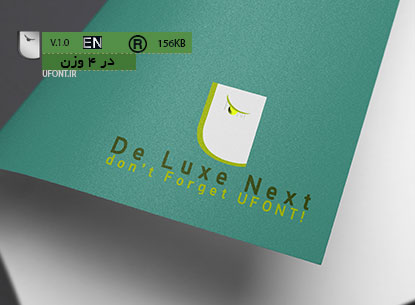
دانلود فونت لاتین De Luxe Next ، نشر 2019
فونت جدید و کلاسیک لاتین با ساختار لوکس و مناسب برای استفاده در طرح های خاص
یکی از مهمترین ویژگی های این فونت خوانا بودن و ساختار بسیار ساده است که موجب شده برای استفاده در متن نیز مناسب باشد ، این فونت ، امسال بصورت رسمی در 4 وزن منتشر شد که هم اکنون می توانید آن را از یوفونت بصورت رایگان ، دریافت کنید ، با ما بروز باشید ! 🙂
فونت لاتین مجموعه دزدان دریایی کارائیب
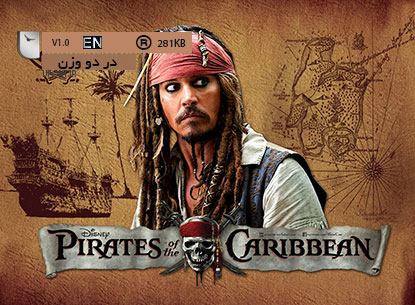
فونت لاتین مجموعه دزدان دریایی کارائیب
فونت لاتین مجموعه فیلم های دزدان دریایی کارائیب ، این فونت زیبای لاتین ، که جزو فونت های خاص دسته بندی میشود نیازی به توضیحات اضافه ندارد ، هم اکنون فونت لاتین مجموعه فیلم های دزدان دریایی کارائیب با همین نام یعنی : Pirates of the Caribbean از یوفونت در دسترس است
دانلود مجموعه فونت و آیکن hello christmas
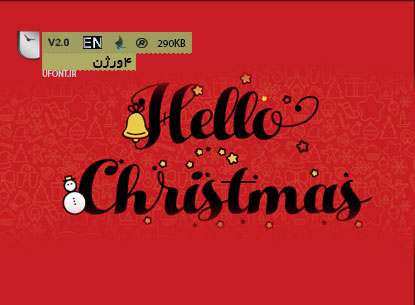
دانلود مجموعه فونت و آیکن hello christmas
دانلود مجموعه فونت و آیکن hello christmas ، مجموعه ای بی نظیر شامل آیکن ، فونت و سمبل های مناسبتی کریسمس
فوق العاده با ارزش ، کاربردی و کمیاب ، با توجه به نزدیک بودن کریسمس مطمئنا برای طراحان عزیز این دست فونت ها بسیار کاربرد دارد
این مجموعه شامل آیکن های مربوط به کریسمس در دو وزن می باشد و بصورت وکتور تا اندازه بی نهایت بدون افت کیفیت قابلیت بزرگنمایی دارند
پیشنمایش فونت
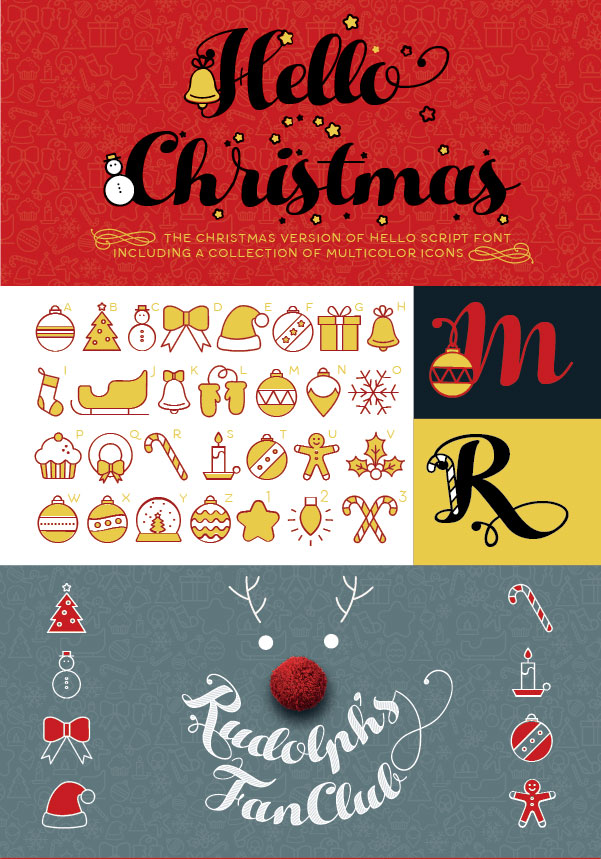
دانلود مجموعه فونت و آیکن hello christmas
-مناسب طراحی آیکن های سایت
-مناسب طراحی های مناسبتی کریسمس
-ساختاری پیچیده و گرافیکی
-مناسب تایپوگرافی
دانلود فونت miraculous and christmas
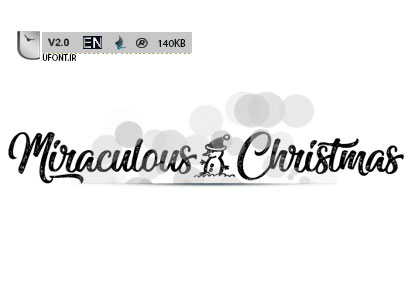
دانلود فونت miraculous and christmas
دانلود فونت miraculous and christmas ، فونتی مناسبتی با اِلِمان های مربوط به کریسمس و هم چنین ساختاری پیچیده با استایل دستنویس
در فونت miraculous and christmas حروف کوچک و بزرگ با هم در ارتباط می باشد پس هنگام استفاده از این فونت حتما به نحوه استفاده از حروف کوچک و بزرگ دقت نمایید چرا که تاثیر بسیاری در خروجی کار دارد همچنین فارق از گرامر و دستور زبان میتوانید به صورت سلیقه ای در طراحی حروف کوچک یا بزرگ را انتخاب نمایید ( فقط جهت طراحی) این راهکار مناسب است و برای نوشتاری بهتر است قواعد گرامر و دستور زبان رعایت گردد
این فونت دارای سمبل های مناسبتی کریسمس نیز می باشد
دانلود فونت فیلم transformers (تبدیل شوندگان)
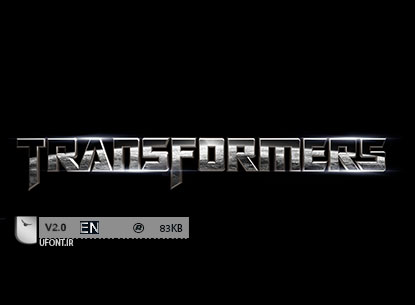
دانلود فونت فیلم transformers (تبدیل شوندگان)
دانلود فونت فیلم transformers (تبدیل شوندگان) ، فونت بکار رفته در لوگوتایپ فیلم تبدیل شوندگان را میتوانید هم اکنون از بروز ترین مرکز دانلود فونت دریافت نمایید
دانلود فونت رسمی جام جهانی 2018 روسیه
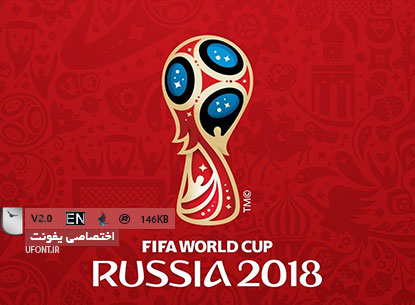
دانلود فونت رسمی جام جهانی 2018 روسیه
دانلود فونت رسمی جام جهانی 2018 روسیه فونت لاتین رسمی مربوط به پوستر ها و کارهای گرافیکی جام جهانی 2018 روسیه هم اکنون از یوفونت در دسترس می باشد
این فونت بصورت رسمی از طرف فیفا در پوستر تایید شده مورد استفاده قرار گرفته و نسخه ای که از یوفونت منتشر می گردد فونت رسمی و بدون دستکاری است که بصورت رایگان در اختیار مخاطبین عزیزمان قرار می گیرد ، نام این فونت Dusha می باشد
ساختار این فونت استاندارد و فانتزی است و چینشی فوق العاده حرفه ای و زیبا دارد
فونت رسمی لوگوتایپ شرکت یاهو
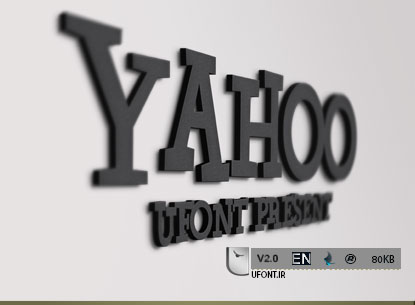
فونت رسمی لوگوتایپ شرکت یاهو
فونت رسمی لوگوتایپ شرکت یاهو ، فونت رسمی استفاده شده در لوگو و لوگوتایپ شرکت یاهو ، این کمپانی محبوب را تقریبا همگی می شناسند و در روز چندین بار به لوگو این کمپانی برخورد می کنند
هم اکنون فونت لوگوی یاهو YAHOO در اختیار شماست ، ساختار این فونت نا متعارف است و کلمات با چینش فانتزی و کمی به هم ریخته در کنار یکدیگر جای می گیرند اما به لطف طراحی اصولی ، در پشت صحنه و عدم خروج از نظم و یکپارچگی تعریف شده برای یک نوشته با نگاه به این به هم ریختگی زیبایی را در قلب این بهم ریختگی می بینید
طراح این فونت با اصول طراحی بسیار آشنا بوده است و در کل فونتی عالی با چینش منظم از خود به یادگار گذاشته است که در دسته فونت های فانتزی لاتین قرار می گیرد ، لذت ببرید
فونت لاتین PowerFull
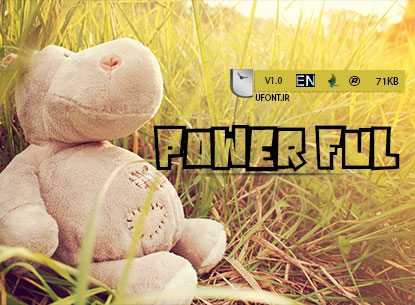
فونت لاتین PowerFull
فونت لاتین PowerFull ، فونت خاص و کاربردی ، دارای ساختار فانتزی و کلمات به هم چسبیده و تو خالی
این دست فونت های فانتزی ویژه طراحی هستند و در کارهای گرافیکی بسیار بکار می آید ، پس این فونت زیبا را از دست ندهید
فونت فارسی فانتزی (پکیج)
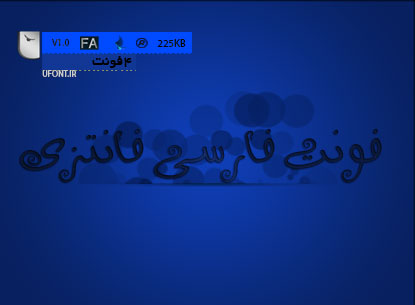
فونت فارسی فانتزی (پکیج)
فونت فارسی فانتزی (پکیج) ، مجموعه 4 عدد فونت های فانتزی با ساختار کودکانه فونت هایی خاص که مطمئنا یک گرافیست در آرشیو خود می بایست این دست فونت ها را داشته باشد ، هم اکنون از یوفونت تقدیم حضورتان می شود لذت ببرید
دانلود فونت لاتین tom and jerry
دانلود فونت لاتین tom and jerry ، نیاز به معرفی و یا توضیح خاصی نیست 🙂 هم اکنون فونت برنامه کودک تام و جرری (موش و گربه) از یوفونت در دسترس شماست